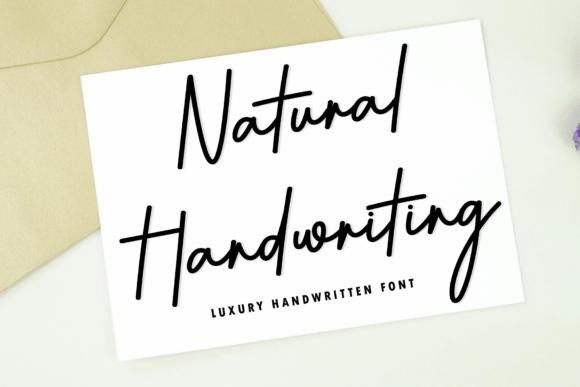
Natural Handwriting
適切なデザイン要素を見つけるのは難しい場合がありますが、Natural Handwritingは作品を即座に引き立てる優れたコレクションを提供します。
POD(オンデマンド印刷)製品、結婚式の招待状、またはソーシャルメディアのグラフィックを作成している場合でも、Natural Handwritingは理想的です。